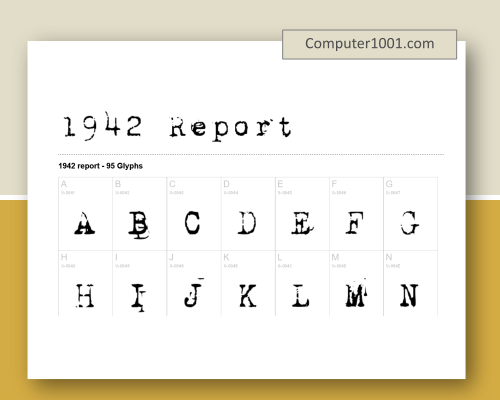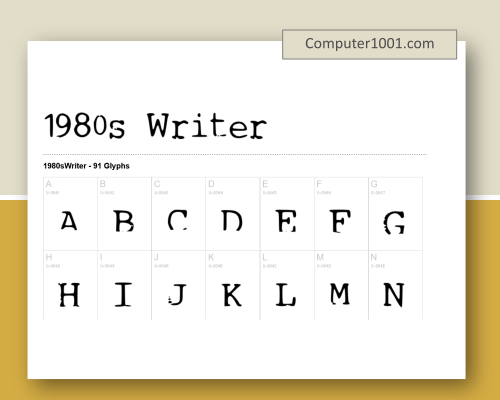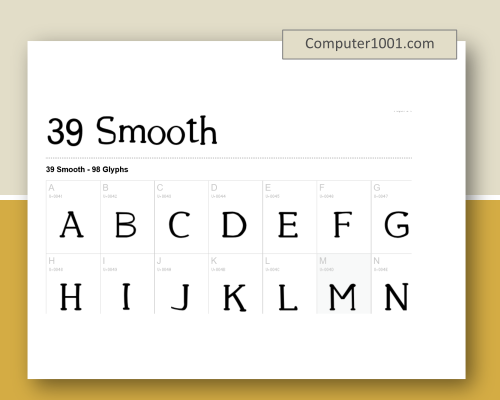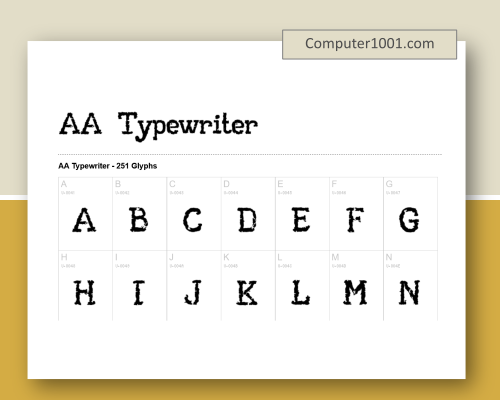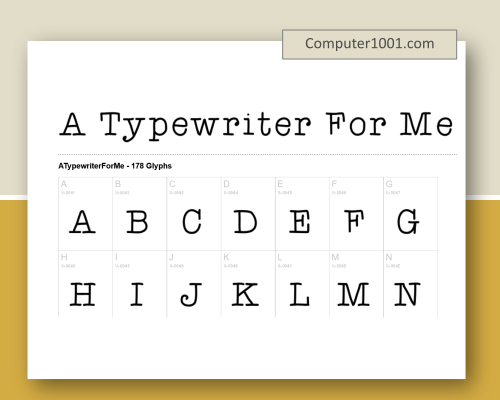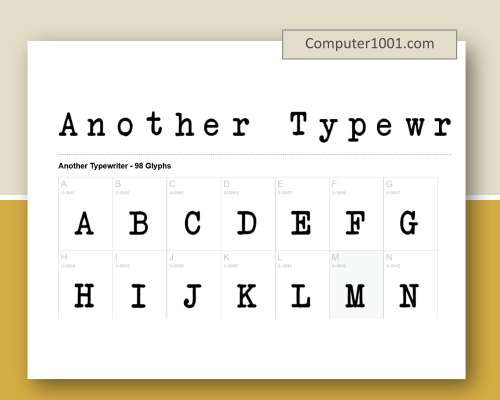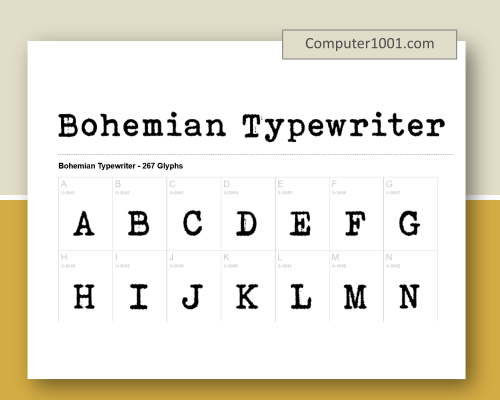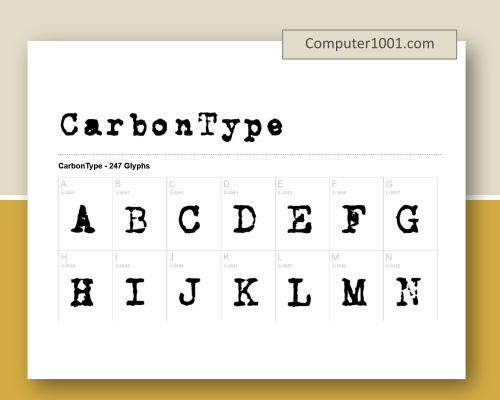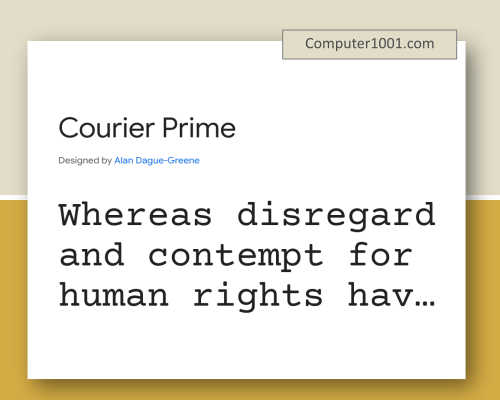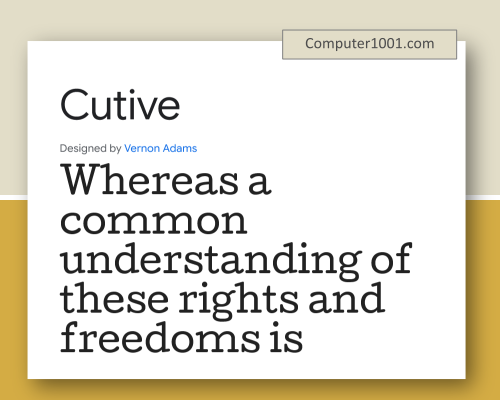
42 Font Mesin Ketik Gratis
Font Mesin Ketik Google dan Canva
Kumpulan font ini cocok untuk desain korporat yang lebih tradisional, serta berbagai proyek kreatif.
Courier Prime
Courier Prime adalah font monospace, dimana setiap karakter memiliki lebar yang sama. Font ini dirancang khusus untuk skenario film. Ketebalan huruf tebalnya sedikit lebih gelap dan huruf miringnya lebih kursif.
Cutive
Cutive juga merupakan font monospace yang didasarkan pada sejumlah jenis huruf mesin ketik klasik, khususnya jenis huruf Executive milik IBM dan Smith-Premier.
Selain untuk kata-kata dan kalimat dalam suatu teks, font ini juga bisa untuk ukuran besar pada heading atau poster.
Lekton
Font Lekton terinspirasi oleh jenis huruf yang digunakan pada mesin ketik Olivetti. Cocok untuk anda yang ingin huruf mesin tik yang bentuknya kurus dan tinggi.
Nixie One
Desain font serif ini terinspirasi dari huruf pada papan nama lampu neon dan mesin ketik.
Special Elite
Special Elite meniru model mesin ketik Smith Corona Special Elite dan Remington Noiseless, dengan efek grunge bertinta.
Font mesin ketik ini cocok untuk membuat desain nuansa jadul di Canva, Google Docs, Google Slides, dan Google Sheets.
Syne Mono
Syne Mono adalah font yang lebar, dengan lengkungan yang tidak beraturan pada setiap karakter. Huruf g kecil pada Syne Mono memiliki ekor yang terpotong.
Walaupun bentuknya berantakan, font ini tetap kelihatan indah, baik dalam ukuran kecil maupun besar.
Font Mesin Ketik Dafont
Kebanyakan font di Dafont cocok untuk desain yang artistik dan kreatif, seperti untuk packaging produk, cover video, cover buku, cover Wattpad, poster, dan postingan sosial media.
1942 Report
Font 1942 Report memiliki tampilan tulisan seperti dalam dokumen sejarah atau dokumen rahasia, terutama di sekitar tahun 1940an. Beberapa karakternya seolah-olah terketik 2 kali. Contoh: huruf B,E, I, J, dan M.
1980s Writer
Pada 1980s Writer, bagian bawah huruf besar ABCDEFG kelihatan terkikis, demikian juga pada sebagian huruf kecil.
39 Smooth
Font ini adalah gabungan gaya mesin tik dan tulisan tangan anak-anak yang tidak beraturan.
A Typewriter For Me
Font ini dibuat dengan aplikasi iFontMaker untuk iPad. Tulisannya memiliki tampilan yang terkesan lucu dan imut; dengan kaki huruf F besar yang terpotong.
AA Typewriter
Font ini dibuat berdasarkan mesin ketik Amerika kuno yang dipadukan dengan garis-garis modern yang jelas sehingga mudah dibaca dalam ukuran kecil.
Another Typewriter
Font mesin tik yang tinggi kurus dengan jarak antar huruf yang lebar.
Bohemian Typewriter
Font ini digunakan untuk teks dalam film Greyhound dan serial dokumenter The Untold History of the United States.
CarbonType
Karakter pada font ini seperti hasil ketikan mesin ketik manual yang menggunakan kertas karbon.
Daisy Wheel
Daisy Wheel adalah font mesin ketik jadul yang juga memberi kesan kekinian.
F25 Executive
Desain font ini terinpirasi oleh tulisan pada dokumen tahun 50an dan 60an, yang menggunakan mesin tik IBM Executive.
FB Remington
FB Remington juga memiliki kumpulan huruf aksen.
Fragment Core
Karakter pada font Fragment Core memiliki tampilan yang aesthetic dan elegan. Cocok untuk desain yang artistik, seperti undangan pernikahan.
Hammer Keys
Hammer Keys adalah font yang unik, dimana setiap huruf terdiri dari huruf kapital dan huruf kecil, yang disusun bertingkat atas dan bawah. Untuk angka 1-9 bergabung dengan tanda kurung, tanda seru, dan tanda lainnya.
Hammer Keys Font Mesin Ketik Dafont
Jackwrite
Font ini memiliki 3 ketebalan: normal, bold, dan thin.
Jackwrite Font Mesin Ketik Dafont
Kingthings Trypewriter
Font ini juga memiliki efek ketikan yang menggunakan kertas karbon, sehingga ada bayangan pada setiap karakter.
Kingthings Trypewriter Font Mesin Ketik Dafont
Leorio
Leorio juga font mesin ketik yang memiliki rasa kekinian dan imut.
Leorio Font Mesin Ketik Dafont
Limetart
Font tulisan tangan yang meniru gaya huruf mesin tik. Cocok untuk desain yang lucu untuk anak-anak dan sebagainya.
Limetart Font Mesin Ketik Dafont
Mom’s Typewriter
Mom’s Typewriter adalah font yang populer, dengan huruf b dan g kecil kelihatan kabur terkena tinta yang tebal.
Font ini tidak memiliki angka 0 dan 1, sama seperti pada papan tuts mesin ketik manual jaman dulu. Tapi kita bisa mengakalinya dengan huruf besar O dan huruf kecil L (l).
Mom's Typewriter Font Mesin Ketik Dafont
My Old Remington
Pada beberapa huruf dan angka My Old Remington terdapat titik-titik kecil yang membuat desain kelihatan makin unik.
My Old Remington Font Mesin Ketik Dafont
My type of font
Seperti contoh pada gambar, beberapa karakter pada font ini tidak memiliki baseline yang sama. Ada sebagian yang lebih tinggi dari karakter yang lain, sehingga tulisannya akan terlihat naik turun. Font tipe ini cocok untuk desain yang ingin terkesan playful, seperti desain untuk anak-anak.
My type of Font Mesin Ketik Dafont
Old Newspaper Types
Seperti namanya, tampilan font ini seperti headline pada surat kabar jadul.
Old Newspaper Types Font Mesin Ketik Dafont
Remington Noiseless
Karakter pada Remington Noiseless memiliki jarak yang berdekatan, dengan huruf kecil m yang kakinya menyatu.
Remington Noiseless Font Mesin Ketik Dafont
Rough Typewriter
Memiliki 4 style: regular, italic, bold, dan bold italic. Juga memiliki ligatur otomatis untuk huruf ganda aa, bb, cc, ee, dan lain-lain.
Rough Typewriter Font Mesin Ketik Dafont
Splendid 66
Font ini memiliki 3 ketebalan: normal, bold, dan pudar.
Splendid 66 Font Mesin Ketik Dafont
Stampwriter-Kit
Huruf pada font ini semuanya huruf besar, dengan ketebalan yang berbeda.
Stampwriter-Kit Font Mesin Ketik Dafont
Tox Typewriter
Dalam ukuran besar, pinggiran karakter Tox Typewriter kelihatan tidak rata.
Tox Typewriter Font Mesin Ketik Dafont
Type Wrong
Type Wrong adalah font mesin ketik yang tebal. Cocok untuk desain poster, thumbnail Youtube, dan lain-lain.
Type Wrong Font Mesin Ketik Dafont
Typewriter – a602
Font ini memiliki huruf bergaya blok yang memberi kesan retro.
Typewriter - a602 Font Mesin Ketik Dafont
Typewriter Condensed
Font sans serif dengan jarak huruf yang berdekatan atau sempit. Cocok untuk desain pada media ukuran kecil, misalnya kartu ucapan, kartu undangan, dan kartu nama.
Typewriter Condensed Font Mesin Ketik Dafont
Typewriter Oldstyle
Karakter pada font Typewriter Oldstyle memiliki tampilan yang meliuk dengan nuansa jadul yang kuat. Mirip tulisan pada halaman novel klasik Ernest Hemingway, Jane Austen, dan Charles Dickens.
Typewriter Oldstyle Font Mesin Ketik Dafont
Typewriter Royal 200
Font ini memiliki 3 style, yaitu normal, bold, dan trashed yang berupa huruf tertimpa.
Typewriter Royal 200 Font Mesin Ketik Dafont
Uncle Typewriter
Font ini memiliki desain yang unik. Huruf kecilnya terkesan kotor dan berantakan. Sebagian huruf besar tercoret, hanya huruf D, E, dan M yang masih bisa terbaca. Cocok untuk desain yang bernuansa grunge.
Uncle Typewriter Font Mesin Ketik Dafont
Underwood 1913
Font mesin tik yang tinggi kurus, dengan nuansa jadul yang kental. Angka 9 seperti terketik 2 kali.
Underwood 1913 Font Mesin Ketik Dafont
Veteran Typewriter
Sebagian karakter pada font ini memiliki efek seperti tergores atau terhapus karena dimakan waktu.
Veteran Typewriter Font Mesin Ketik Dafont
VT Portable Remington
Karakter pada font ini sama seperti font Remington lainnya, namun ada beberapa karakter yang tidak tercetak sempurna. Contohnya huruf V pada gambar ini.
VT Portable Remington Font Mesin Ketik Dafont
X Typewriter
X Typewriter adalah font monospace yang indah dengan jarak huruf yang berdekatan. Font ini juga memiliki simbol mata uang, operator matematika, dan tanda baca.
X Typewriter Font Mesin Ketik Dafont
Penutup
Font mesin ketik yang sudah ada di Microsoft Word, Excel, dan PowerPoint adalah berikut ini:
• Bell MT
• Bookman Old Style
• Courrier New
• Lucida Sans Typerwriter
• Times New Roman
Tulisannya yang kayak mesin ketik cocok untuk membuat penomoran pada invoice, kwitansi, surat jalan, atau dokumen transaksi lainnya.
Namun, bila anda ingin font mesin ketik dengan efek grunge, pupus, atau ada noda tinta pada kertas; maka bisa unduh dan install kumpulan font Dafont di atas.
Font nuansa jadul ini cocok untuk membuat junk journal, scrapbook, desain tema sejarah, literatur klasik, atau desain tema nostalgia yang bernuansa retro.